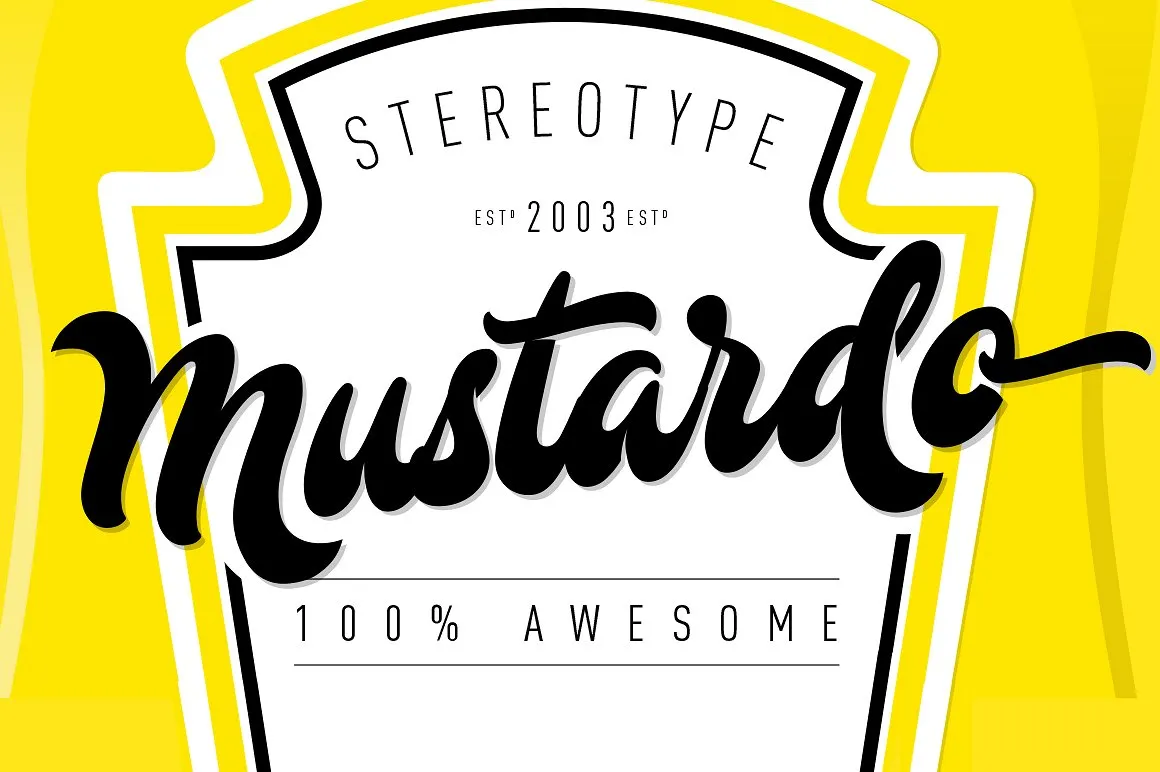
Olá, amigos criativos! Estou aqui para dar uma descrição do Mustardo Font para vocês nesta página de download. Este é um script font gratuito apenas para uso pessoal, mas se você quer usar na sua negócios, há uma versão comercial disponível em www.stereo-type.fr. O Designer StereoType fez este design com todo o seu amor e carinho. Ele adicionou uma variedade de alternativas de letras e ligaturas contextualizadas para permitir que você personalize a fonte para criar um estilo único que combina perfeitamente com qualquer projeto. Clement, também do StereoType, criou esta elegante e versátil fonte script que certamente vai adicionar valor à sua identidade visual e a qualquer design em que for utilizada. Agradeço ao Designer por compartilhar seu talento e esperamos que você também se divirta utilizando este incrível Mustardo Font!